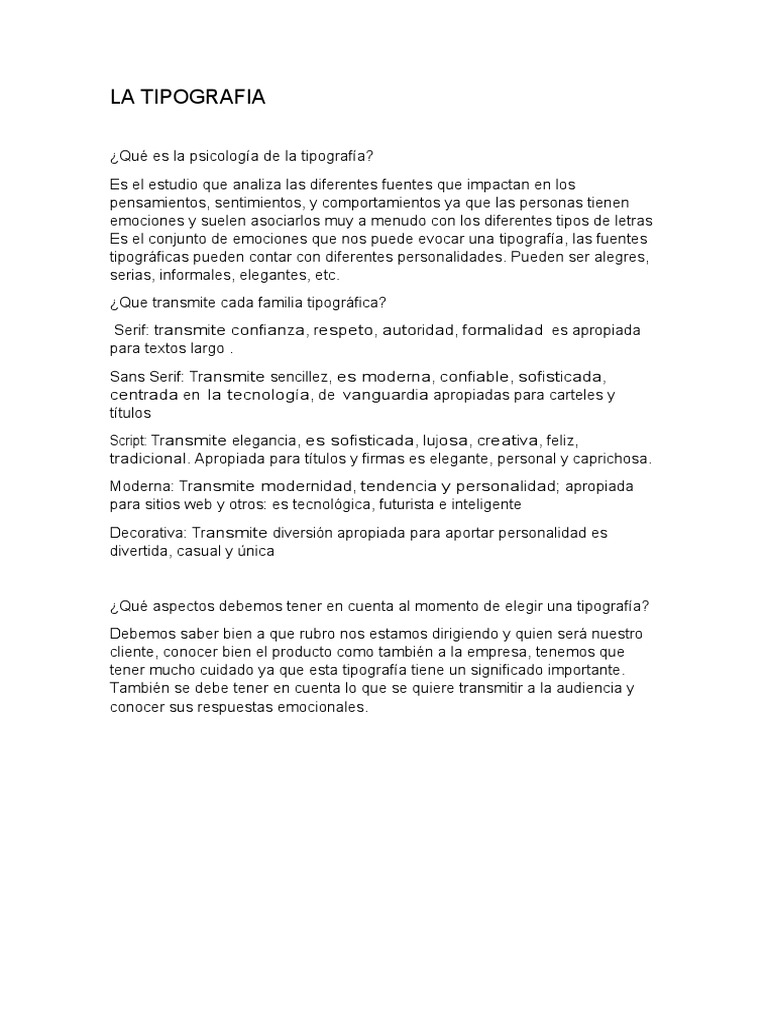
LA TIPOGRAFIA
¿Qué es la psicología de la tipografía?
Es el estudio que analiza las diferentes fuentes que impactan en los
pensamientos, sentimientos, y comportamientos ya que las personas tienen
emociones y suelen asociarlos muy a menudo con los diferentes tipos de letras
Es el conjunto de emociones que nos puede evocar una tipografía, las fuentes
tipográficas pueden contar con diferentes personalidades. Pueden ser alegres,
serias, informales, elegantes, etc.
¿Que transmite cada familia tipográfica?
Serif: transmite confianza, respeto, autoridad, formalidad; es apropiada
para textos largo .
Sans Serif: Transmite sencillez, es moderna, confiable, sofisticada,
centrada en la tecnología, de vanguardia apropiadas para carteles y
títulos
Script: Transmite elegancia, es sofisticada, lujosa, creativa, feliz,
tradicional. Apropiada para títulos y firmas es elegante, personal y caprichosa.
Moderna: Transmite modernidad, tendencia y personalidad; apropiada
para sitios web y otros: es tecnológica, futurista e inteligente
Decorativa: Transmite diversión apropiada para aportar personalidad es
divertida, casual y única
¿Qué aspectos debemos tener en cuenta al momento de elegir una tipografía?
Debemos saber bien a que rubro nos estamos dirigiendo y quien será nuestro
cliente, conocer bien el producto como también a la empresa, tenemos que
tener mucho cuidado ya que esta tipografía tiene un significado importante.
También se debe tener en cuenta lo que se quiere transmitir a la audiencia y
conocer sus respuestas emocionales.